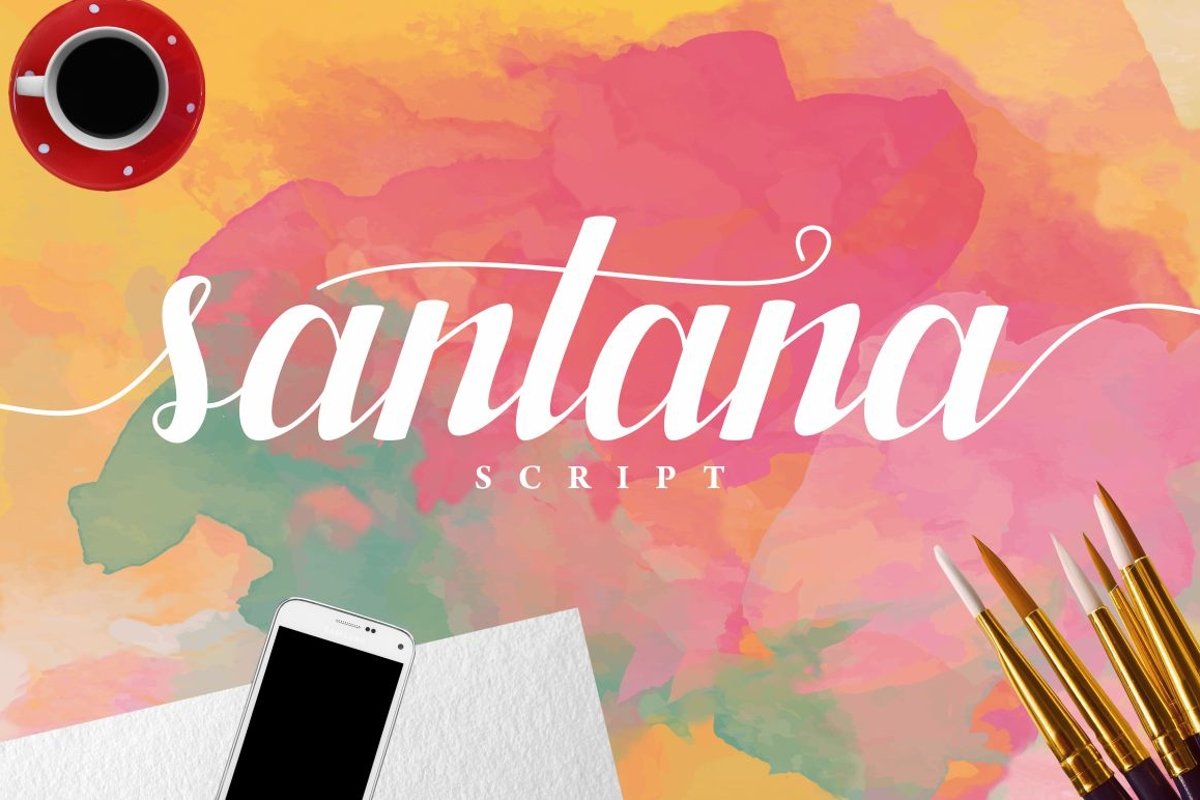
santana script
Script Santana dan script baru modern dengan gaya kaligrafi buatan tangan, karakter dekoratif dan tari dasar! Begitu indah pada undangan seperti kartu ucapan, materi branding, kartu nama, kutipan, poster, dan masih banyak lagi !!
Script Santana